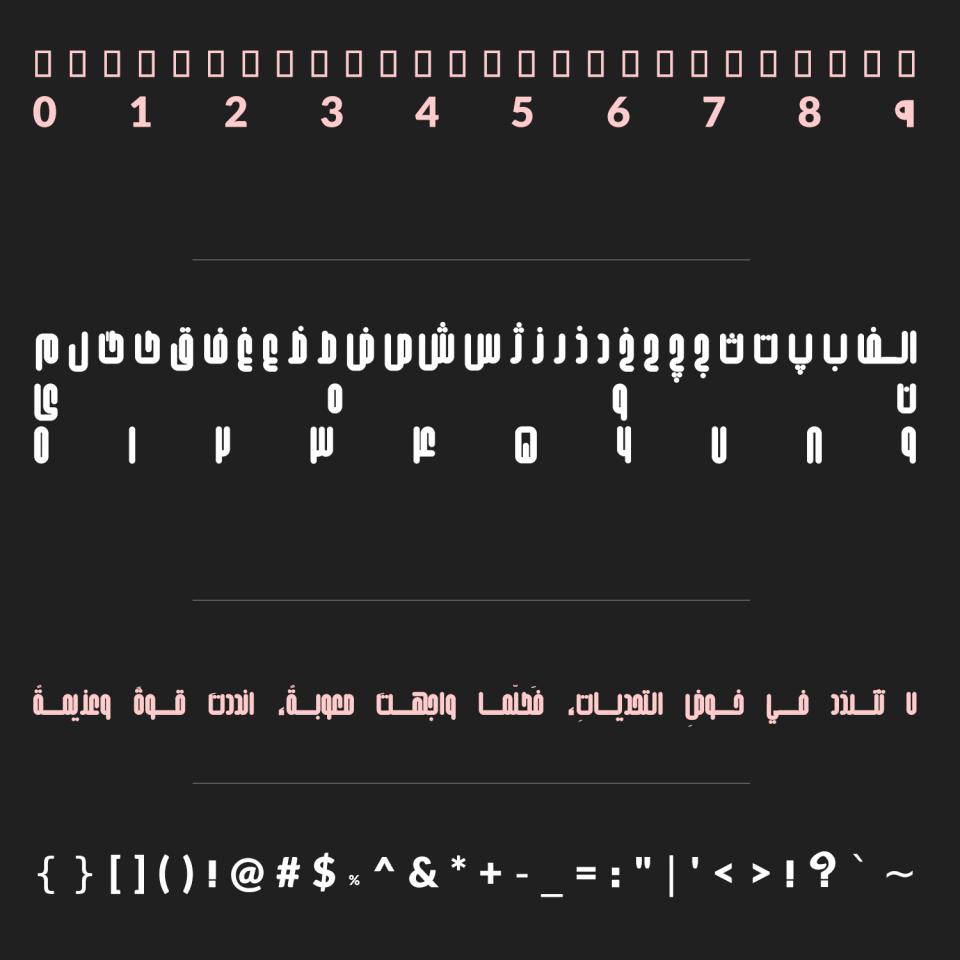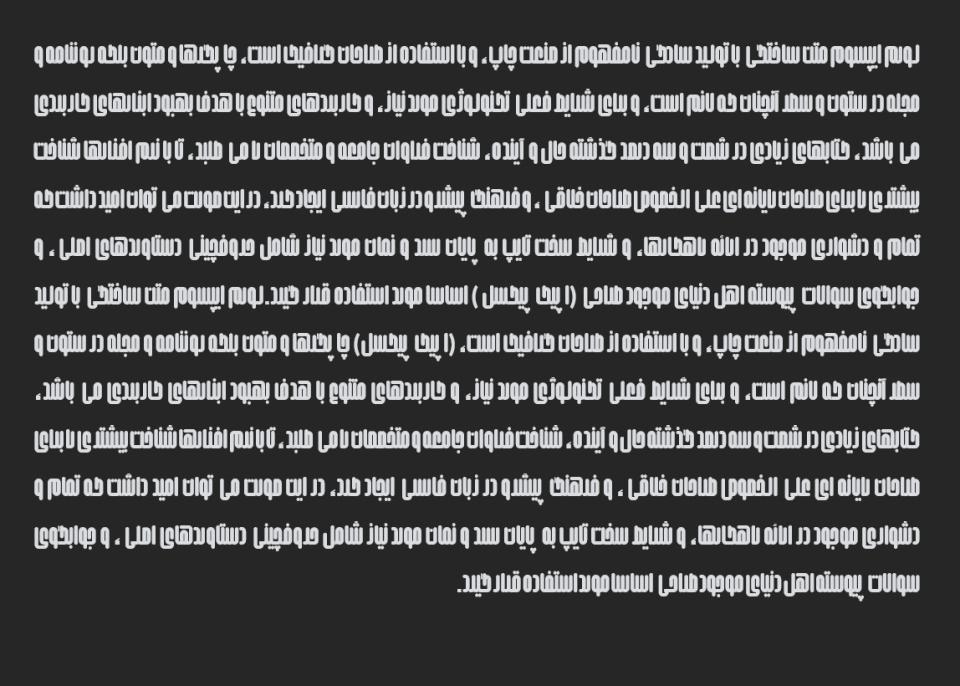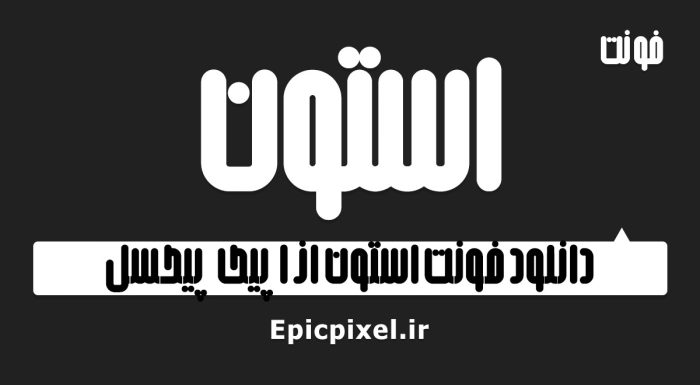
2 فونت استون فارسی Stone
فونت استون ( فونت سنگ ) فارسی، با طراحی خاص و منحصربه فردش، می تونه جلوه ای چشمگیر به نوشته های شما ببخشه. این فونت، با ساختار کشیده و رو به بالایی که داره، حس پویایی و مدرنیته رو القا می کنه و در عین حال، گوشه های کاملاً گرد حروف، لطافت و صمیمیت خاصی به اون می بخشه. این ترکیب منحصربه فرد، باعث میشه فونت استون هم برای عناوین جذاب و تبلیغاتی و هم برای متن های طولانی تر که نیاز به خوانایی بالا دارن، گزینه ای ایده آل باشه.
یکی از ویژگی های برجسته این فونت، خوانایی بالای اونه. طراحی دقیق حروف و فاصله گذاری مناسب بین اونها، باعث میشه چشم به راحتی روی متن حرکت کنه و خواننده خسته نشه. این ویژگی به خصوص در متن های طولانی و محتوای وب که مخاطب ممکنه زمان زیادی رو صرف خوندن اون کنه، اهمیت زیادی داره. فونت استون با وجود ظاهر مدرن، اصالت خط فارسی رو حفظ کرده و این باعث میشه در طیف وسیعی از پروژه ها، از طراحی لوگو و بسته بندی گرفته تا طراحی وب سایت و اپلیکیشن، قابل استفاده باشه.
البته باید به این نکته هم اشاره کرد که به دلیل ساختار کشیده، شاید در اندازه های خیلی کوچک، خوانایی فونت کمی کاهش پیدا کنه. بنابراین، توصیه میشه در طراحی هایی که فضای محدودی دارن، از این فونت با احتیاط استفاده بشه. همچنین، از اونجایی که این فونت رایگان نیست، ممکنه برای برخی افراد محدودیت ایجاد کنه. اما با در نظر گرفتن ویژگی های منحصربه فرد و کاربردهای گسترده ای که داره، سرمایه گذاری برای تهیه ی این فونت می تونه انتخابی هوشمندانه برای طراحان و افرادی باشه که به دنبال کیفیت و تمایز در آثار خودشون هستن. در واقع، فونت استون فارسی، فراتر از یک فونت ساده، ابزاری قدرتمند برای خلق آثار بصری جذاب و ماندگاره.